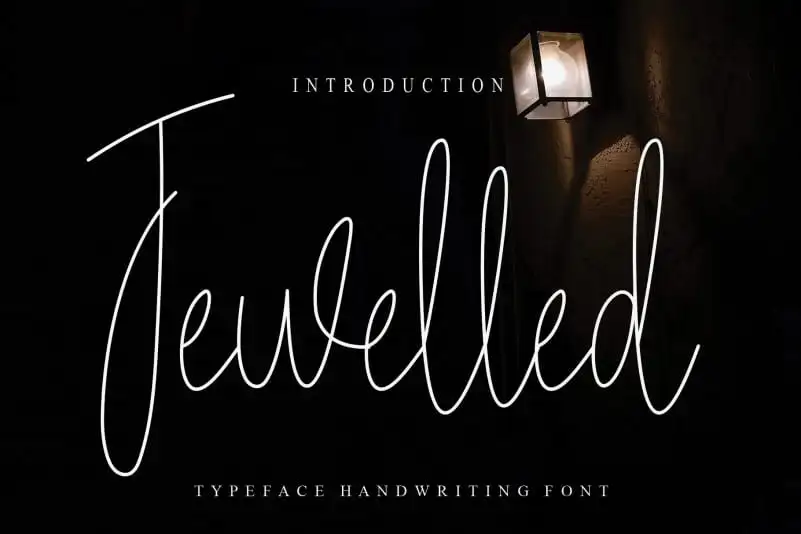
Jewelled Handwritten Font – Download Grátis
A Júpia Fontada é uma elegante escrita cursiva criada pelo Designer CreativeLetter para quem procura adicionar um toque único a seus projetos. Esta fonte não apenas oferece uma experiência visual deslumbrante, mas também traz consigo uma história de criatividade e originalidade. Suas letras curvas fluidas e detalhes delicados dão ao seu design um brilho excepcional. Seja para um projeto de design gráfico, uma publicação online ou até mesmo em uma simples carta pessoal, a Júpia Fontada é perfeita para aqueles que buscam não apenas uma fonte versátil e esteticamente atraente, mas também algo único e memorável. Adquirir esta fonte será como receber um presente especial de criatividade, repleto de detalhes cuidadosamente selecionados para deixar seu design ainda mais brilhante.